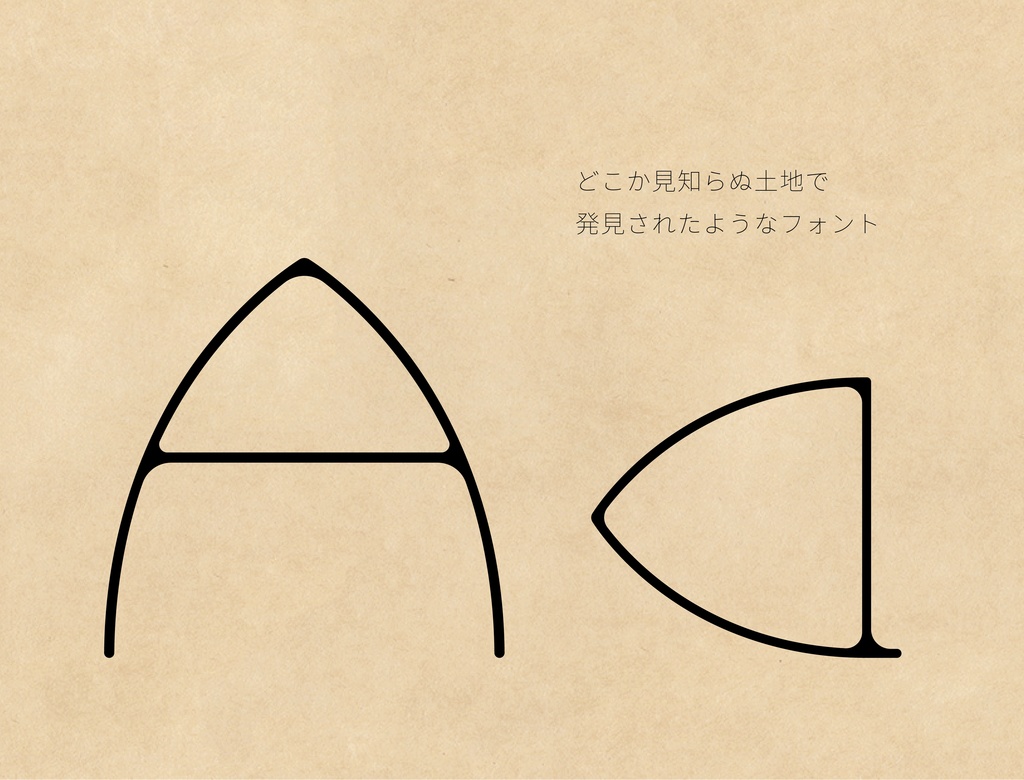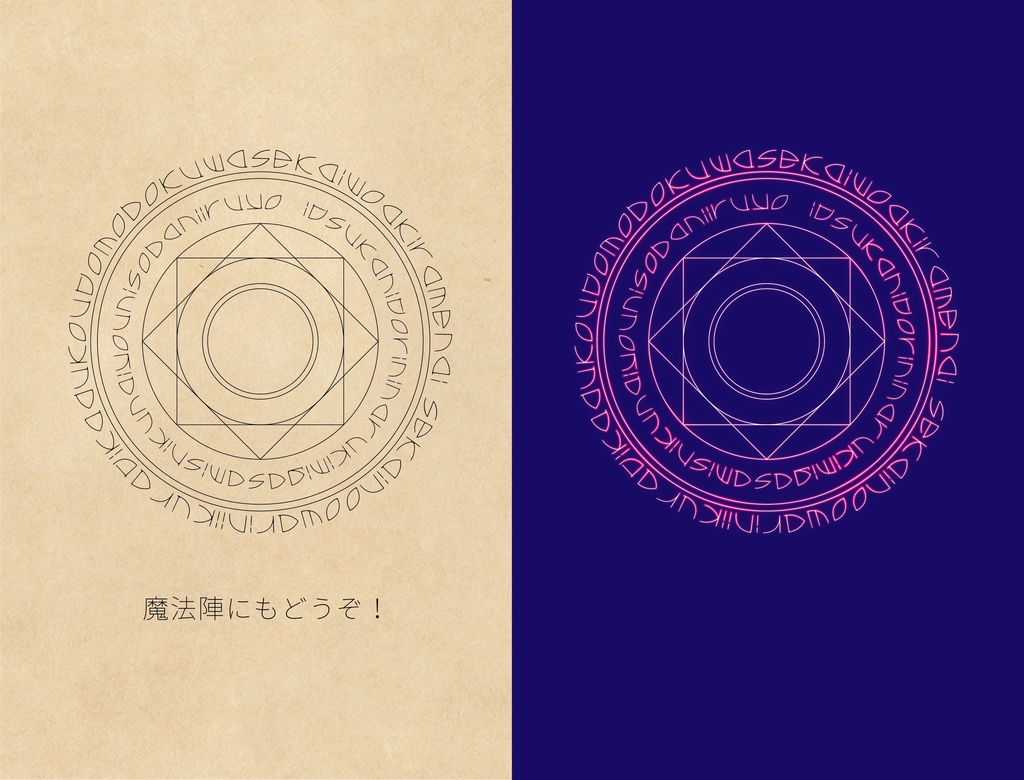
dokokaフォント
【特徴】 コンセプトは「どこかで発見された文字」 見知らぬ土地で出会ったような、ちょっと不思議な感覚のフォントです。 アルファベット大文字と小文字を用意しています。 打つだけであっという間にファンタジーな文書の出来上がり。 円状に打ち込んで魔法陣風にするのもいいかもしれません。 【収録】 大小アルファベット+記号=全56文字 【利用について】 ・個人利用・商用利用OKです。 ただし、本フォントの文字をメインとした商品の販売は禁止です。 ・利用報告は必須ではありませんが、していただけると私が喜びます。 ツイッターアカウント:https://twitter.com/ashitanoayano 【注意事項】 ・フォントファイルの販売・再配布は禁止です。 詳細は同封のテキストファイルをお読みください。 【履歴】 2020.9.1 ver1リリース